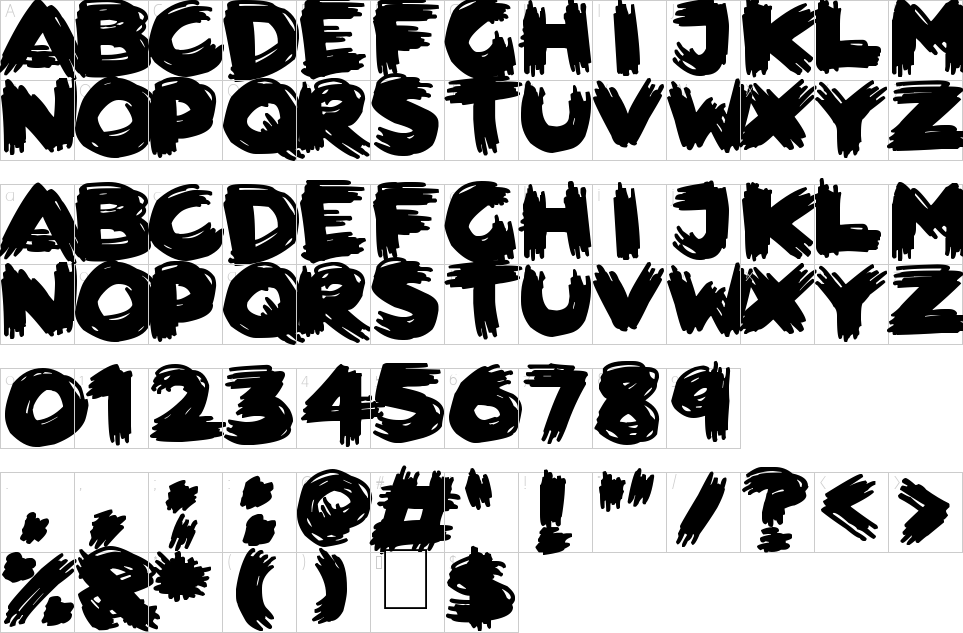
Scribbletastic Brush é uma fonte desenhada por Darrell Flood, disponível gratuitamente tanto para Windows quanto para Mac. Esta fonte é perfeitamente adequada para quem quer adicionar um toque de graça e naturalidade a seus projetos digitais. Com sua aparência suave e desenhada para o estilo de escrita livre, ela permite criar um estilo de escrita espontânea e fluida em suas publicações online ou até mesmo em projetos impressos. Sua popularidade é reconhecida, já que a fonte foi baixada 2,406 vezes, mostrando que muitos profissionais de design compartilham sua paixão pela simplicidade e criatividade que a Scribbletastic Brush oferece. Se você está procurando por uma fonte que ofereça uma maneira fresca de trazer vida aos seus trabalhos digitais, considerar a Scribbletastic Brush pode ser uma excelente escolha.